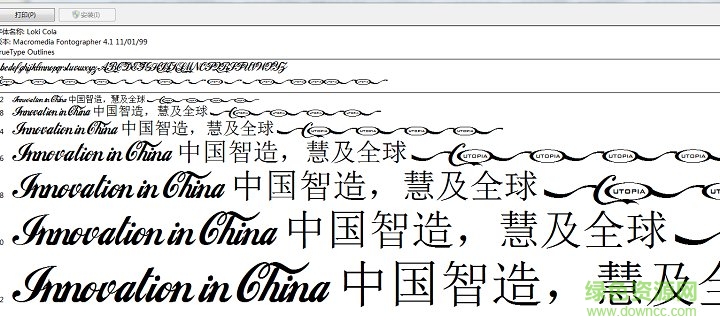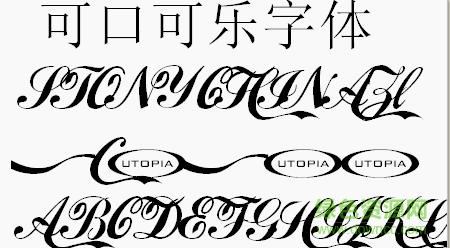
包裝設(shè)計將原有的斯賓瑟字體書寫的白色英文商標(biāo)與最新的設(shè)計元素相結(jié)合,其中包括「可口可樂」品牌專用紅,弧型瓶,以及波浪型飄帶圖案。
新的包裝設(shè)計保留了原有的紅色背景上的斯賓瑟商標(biāo),然而新設(shè)計的白色斯賓瑟商標(biāo)變得更清晰,簡明;其次,「可口可樂」紅色背景中加入了暗紅色弧形線,整體的紅色變得更有深度和動感,并產(chǎn)生了多維的透視效果。